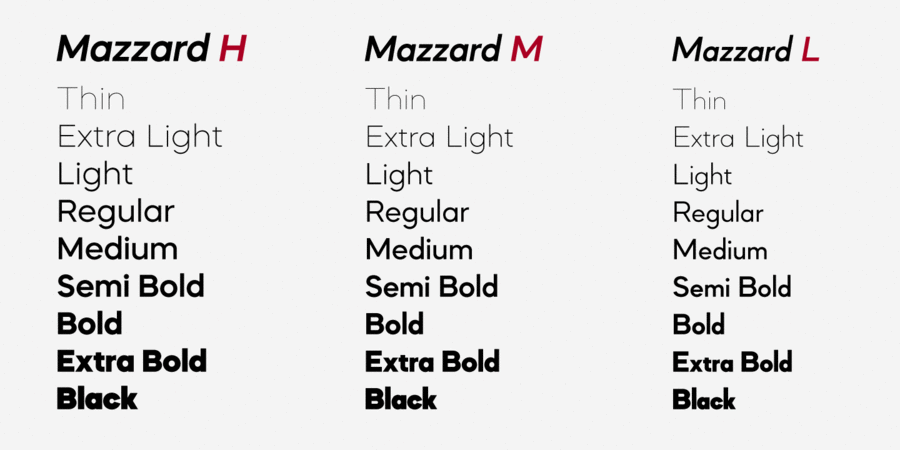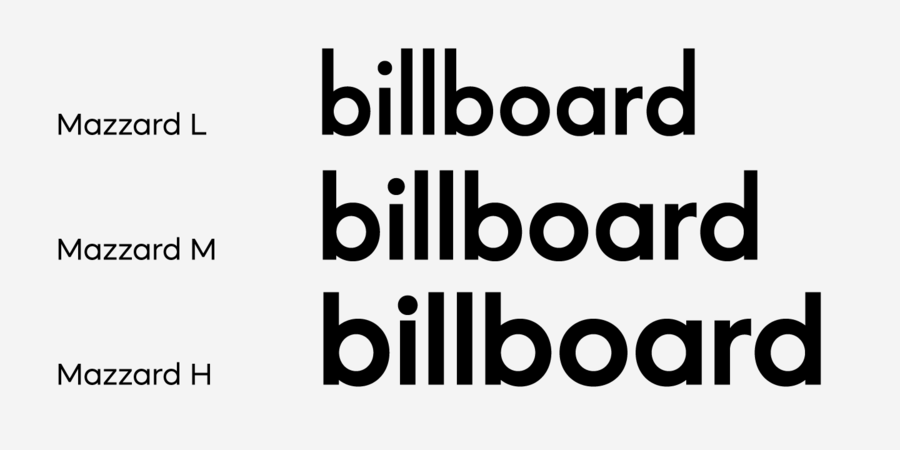
Mazzard M – це частина шрифтового суперсімейства Mazzard.
Суперсімейство складається з трьох геометричних гротесков з різною висотою рядкових знаків.
Mazzard M має широкий спектр підтримки мов та пропонує великій вибір альтернативних гліфів.
Шрифт розробив Олег Ліщук в 2019 році.
журнал, плакат, лендінг, покажчик, табло, код, штамп, квитанція, чек, етикетка, реклама, презентація, банкнота, марка, календарна сітка, обкладинка, пакування, афіша, вивіска, оголошення Адаптованість гарнітури до носіїв:
Асоціації з сімейством шрифтів Mazzard MОсобистість і характер гарнітури:
елементарний, мінімалістичний, точний, рівний, статичний, логічний, лаконічний, стійкий, автоматичний, штучний, холодний, інженерний, міський, різкий, чіткий, креслярський, чистий, сучасний, гострий, тонкий, дротяний, скляний, легкий, прохолодний, ясний, невагомий, прозорий, крихкий, модний, худий, технічний, стабільний, Простий, нейтральний, урбаністичний, зрозумілий, формальний, прагматичний, практичний, твердий, доступний, серйозний, надійний, впевнений, машинний, сильний, самостійний, переконливий, індустріальний, техногенний, обов'язковий, архітектурний, залізний, сталевий, міцний, авторитетний, важливий, мотивуючий, крутий, залізничний, солідний, відповідальний, амбітний, мужній, суворий, добротний, жорсткий, грубий, потужний, значний, товстий, яскравий, помітний, важкий, щільний, тісний, монументальний, активний, гучний, сміливий, пролетарський, крижаний
креслення, дизайн, лосьйон, туалетна вода, мода, небо, прилад, інженер, Місто, наука, архітектура, технології, інновації, девайс, гаджет, хімія, математика, урбаністика, код, конструктор, автоматика, коворкінг, меблі, вода, техніка, робот, банкнота, монета, інструмент, промисловість, верстат, завод, архітектор, тренажери, ремонт, сталевар, новини, двигун, електростанція, енергетика, машинобудування, прес, вагон, страйкбол, сейф, охорона, захист, металургія, взуття, залізниця, екскаватор, прапор, мітинг, блокбастер, бойовик, гра, екшен, вантажівка, вантажоперевезення, далекобійник, мотор, логістика Гарнітура має ознаки стилів: